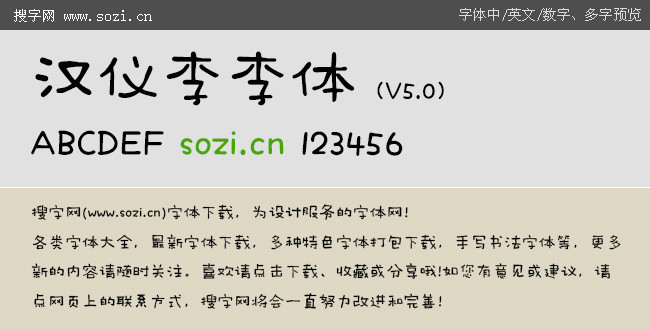
漢儀李李體5.0
搜字網(wǎng)提供一款漢儀李李體中文字體下載,漢儀李李體是一款中文藝術(shù)字體,這款字體設(shè)計(jì)風(fēng)格有點(diǎn)卡通,字形筆畫非常的隨意,具有良好的視覺影響力,適合應(yīng)用于藝術(shù)設(shè)計(jì)、平面宣傳設(shè)計(jì)、書法字帖、海報(bào)設(shè)計(jì)等領(lǐng)域。(本字體為個(gè)人非商用版,如需要商用請(qǐng)聯(lián)系漢儀公司購買版權(quán))